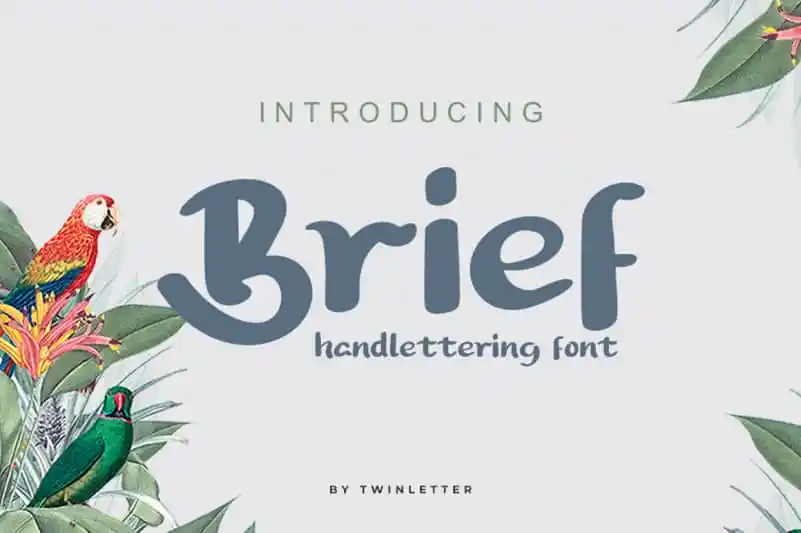
Brief Script Font – Fonte Grátis
Brief Script Font
A Brief Script Font é uma nova adição à gama de fuentes escritas a mão oferecida pelo designer twinletter. Esta tipografia fortemente handwritten captura o charme casual e natural do estilo, tornando-a perfeita para quem busca um equilíbrio entre elegância e acessibilidade. Seu carácter descontraído faz com que ela apareça como uma fonte verdadeiramente down-to-earth, prática e, acima de tudo, extremamente versátil. A Brief está igualmente à vontade em qualquer contexto – seja no fundo cheio ou como um título independente. Com sua simplicidade natural e seu aspecto agradável, essa fonte escrita a mão é uma ótima escolha para designers que buscam manter seus designs minimalistas e sofisticados ao mesmo tempo. É perfeitamente adequada para elementos visuais em páginas de estilo de vida, artigos pessoais ou até mesmo gráficos de marketing digital – seja você usando-a nos fundos complexos ou como o destaque do título da sua próxima campanha online. A Brief Script é uma fonte escrita a mão que você pode adicionar à sua lista de ferramentas de design para complementar qualquer projeto, proporcionando um toque único e autêntico ao seu trabalho.